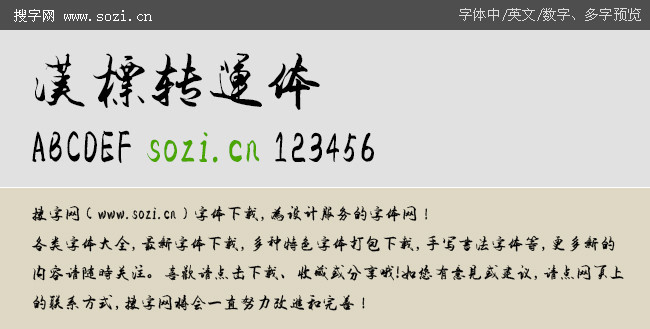
漢標(biāo)轉(zhuǎn)運(yùn)體
搜字網(wǎng)給大家提供一款漢標(biāo)轉(zhuǎn)運(yùn)體中文字體下載,漢標(biāo)轉(zhuǎn)運(yùn)體字體筆畫流暢飛揚(yáng),繁簡結(jié)合,字體左緊右松,開合對比強(qiáng)烈,整套字體有如一氣呵成,行筆迅捷華麗,其個(gè)性浪漫灑脫。適用于標(biāo)題設(shè)計(jì)、包裝設(shè)計(jì)、海報(bào)設(shè)計(jì)等應(yīng)用。(本字體為個(gè)人非商用版,如需要商用請聯(lián)系官方購買版權(quán))